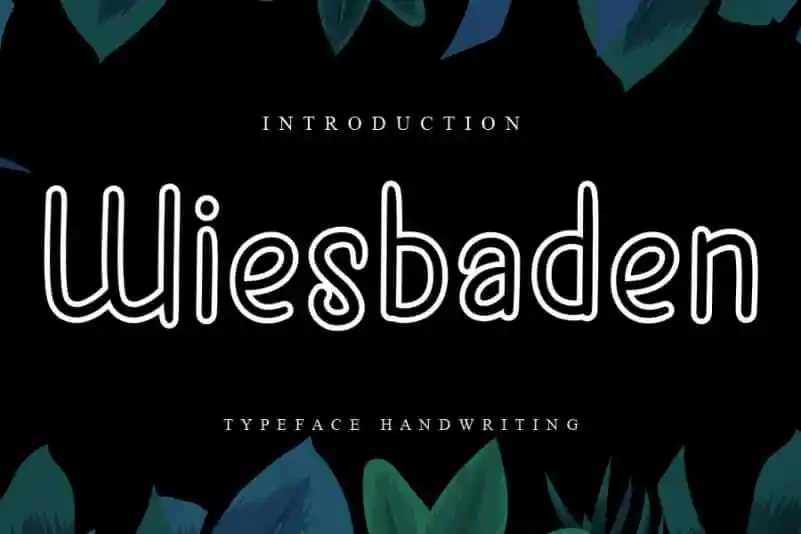
A Wiesbaden Handwritten Font é uma elegante tipografia escrita à mão que se destaca por sua sofisticação e autenticidade perfeita para diversos usos. Perfeita para ambientes de parede, convites de casamento, postagens nas redes sociais, logotipos, anúncios, fotografias e convites e materiais de embalagem, a Wiesbaden Handwritten é uma escolha ideal para aqueles que procuram um ar contemporâneo e autêntico em seu design. Ela traz uma atmosfera envolvente com sua personalização perfeita, fazendo-a uma fonte versátil para diversos projetos visuais. Seja você um designer gráfico ou um amante da arte, a Wiesbaden Handwritten é uma ótima escolha para adicionar um toque único à sua obra de arte visual. Sua simplicidade e sofisticação combinam perfeitamente com diversos estilos e tendências atuais.